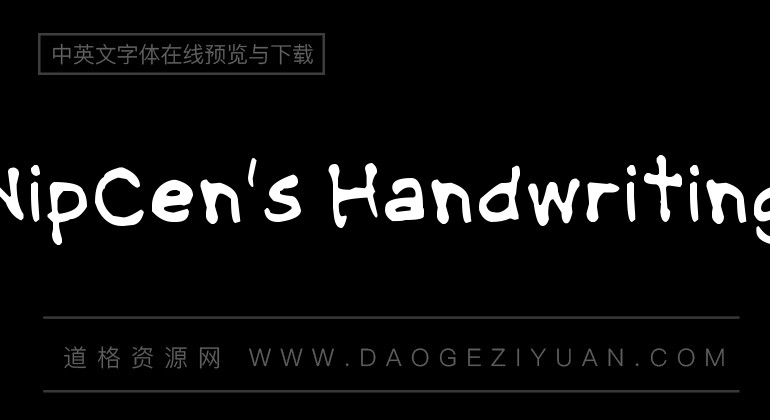
NipCen's Handwriting
NipCen's Handwriting 字体是一款手写字体,它具有清晰的笔画和自然的手写感,可以在印刷品或网络上使用。它的特点是字体的大小可以自由调整,字体的质量不会受到影响,这使得它成为一款非常实用的字体。NipCen's Handwriting 字体也可以用于电子邮件,社交媒体,网页,展示文稿和其他文本。它还可以在桌面出版,印刷品和展示中使用。
NipCen's Handwriting是一款非常不错的手写艺术字体,具有很好的视觉感,适合于文化类的宣传设计、商业类品牌的广告和产品包装设计以及个性化文字排版等较多场景。